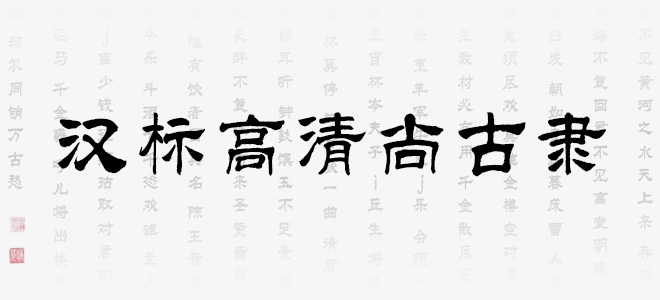
漢標高清尚古隸是一款帶有書法味道的純毛筆手寫字體,參考古代隸書精華融入現(xiàn)代美感,字型偏扁方,筆畫中也減少了過多的處理和筆勢,厚重、飽滿。因為是純手寫的原因,它獨特的氣質(zhì)更與其他字體不同,看似統(tǒng)一,其實各有各的味道,每個字都可以獨具風(fēng)情。適合于文化類的宣傳設(shè)計、商業(yè)類品牌的廣告和產(chǎn)品包裝設(shè)計以及個性化文字排版等較多場景。
漢標高清尚古隸